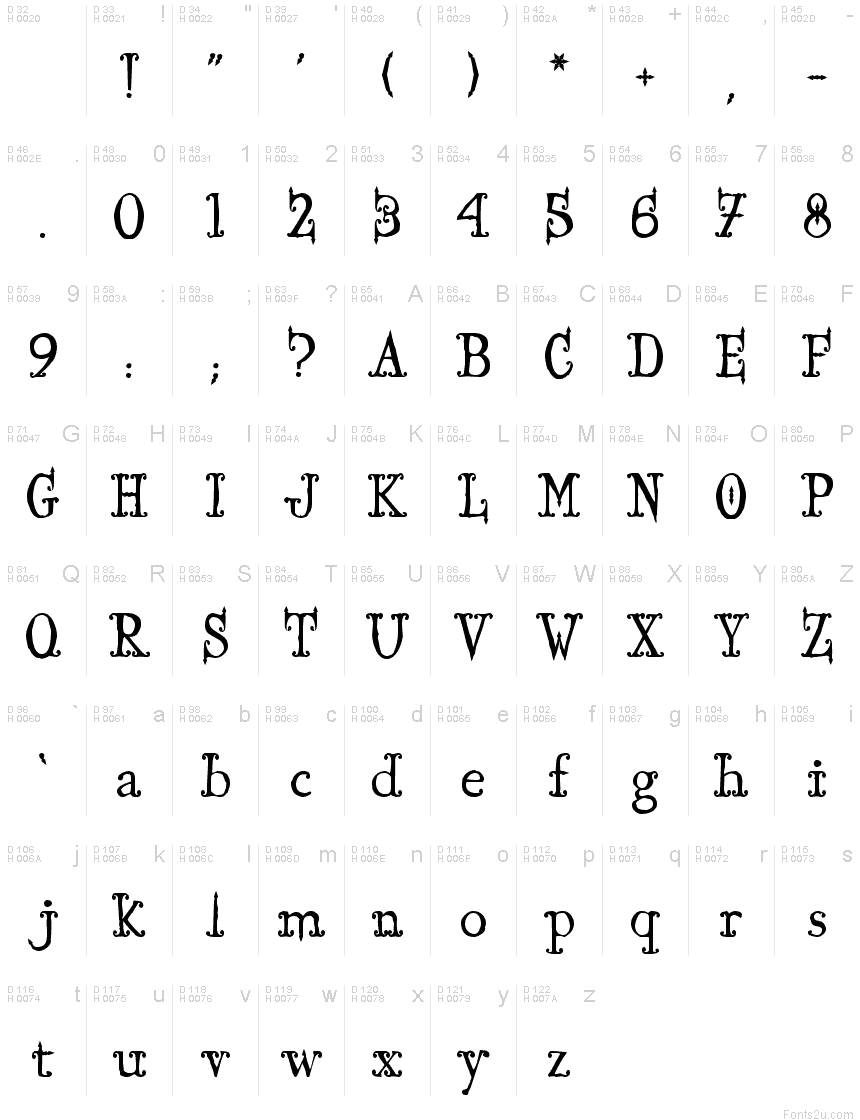
Písmo Ironworks od Davida F. Nalleho je bezplatné dekorativní patkové písmo v retro stylu. Silné tahy připomínající inkoust a zatočené patky mu dodávají pocit kovaného železa, jako byste četli starý hostinský štít nebo viktoriánský cirkusový plakát. Písmena jsou posazena těsně u sebe a vytvářejí hustý, texturovaný tvar slova, který okamžitě upoutá pozornost.
S písmem Ironworks dodáte logům, obálkám knih, fantasy mapám, herním titulům, plakátům a pozvánkám na akce bohatý, starobylý a příběhový nádech. Toto bezplatné písmo vynikne především ve větších velikostech, kde mohou jeho svérázné kudrlinky a robustní tvary volně dýchat; v hlavním textu ho zkombinujte s jednoduchým bezpatkovým písmem, aby zůstala zachována čitelnost, zatímco nadpis bude vyprávět příběh.